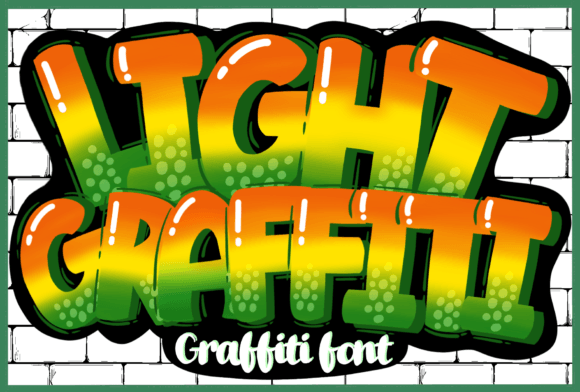
Light Graffiti Font
Light Graffiti Font – الخط المثالي لإبداع فريد ومضيء!
حوّل تصاميمك إلى أعمال فنية متألقة مع Light Graffiti Font، الخط الذي يحاكي تأثير الكتابة بالضوء بأسلوب عصري وجذاب. يتميز هذا الخط بتصميم ديناميكي مستوحى من فن الجرافيتي المضيء، مما يجعله مثاليًا لمشاريع التصميم الجريئة والمبتكرة.
✅ مظهر نابض بالحياة يشبه تأثيرات الإضاءة الحقيقية
✅ مناسب لتصميم الشعارات، البوسترات، وأغلفة الألبومات
أطلق العنان لإبداعك وأضف لمسة من التألق إلى تصاميمك مع Light Graffiti Font! ✨????